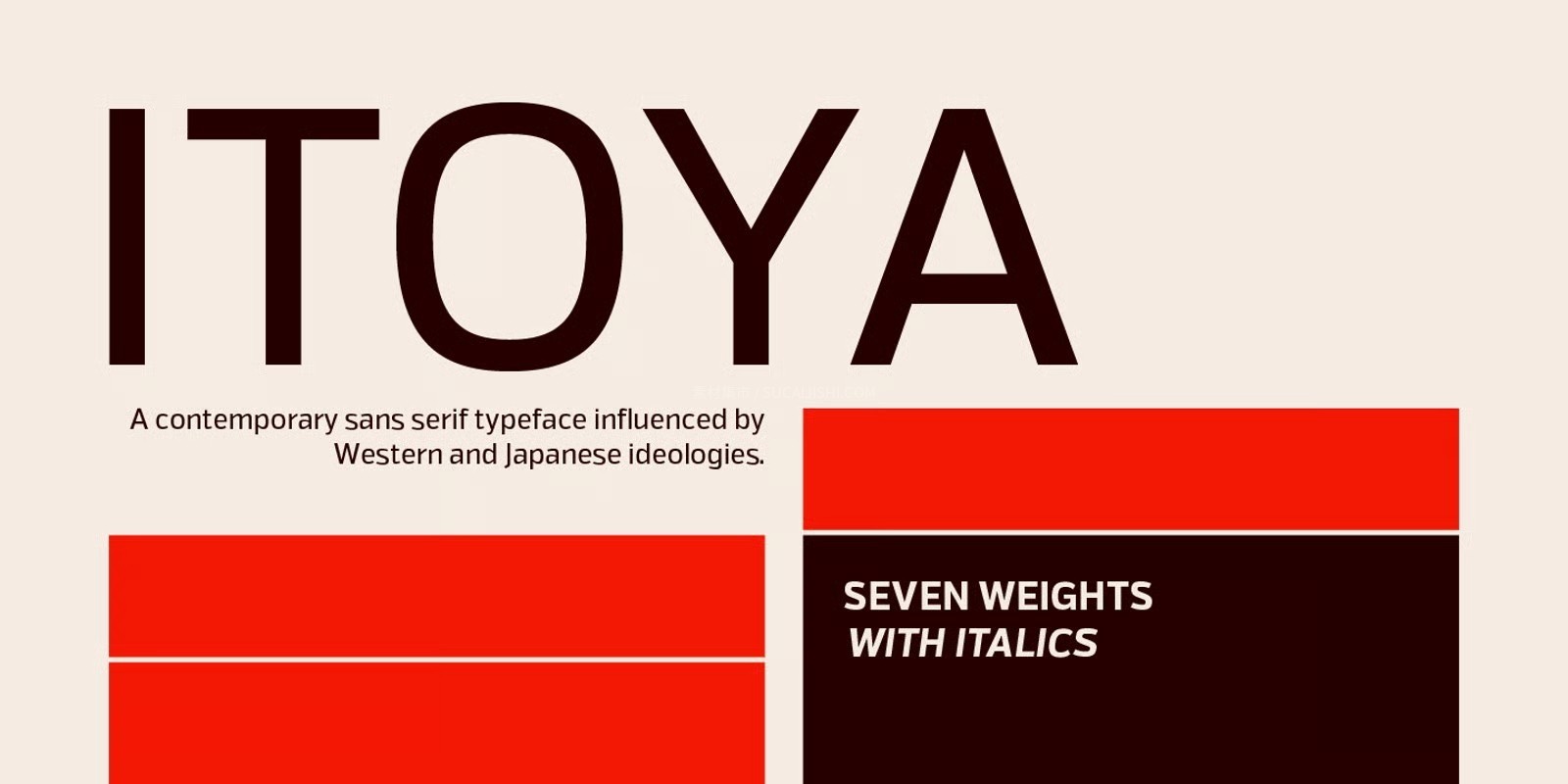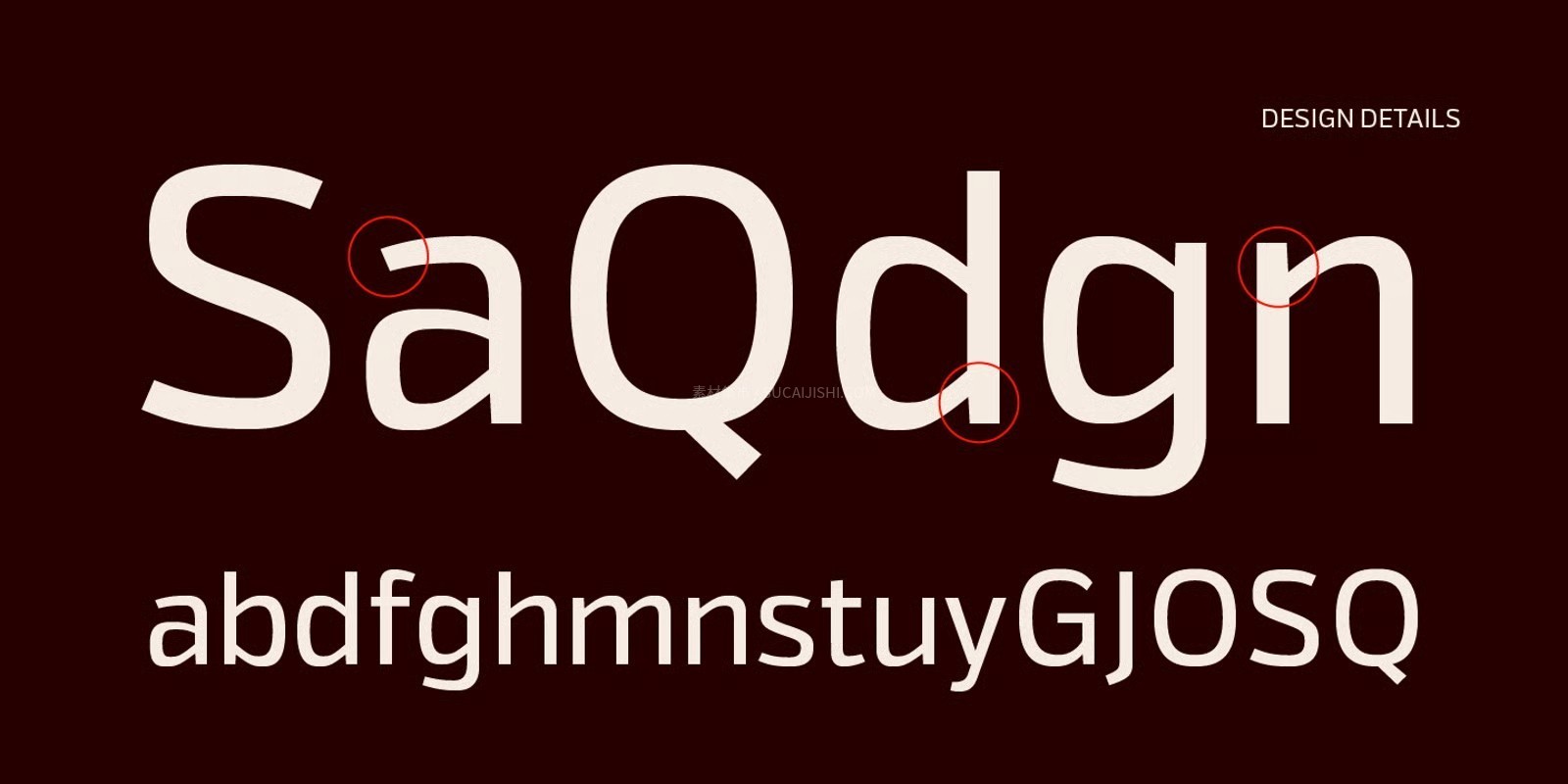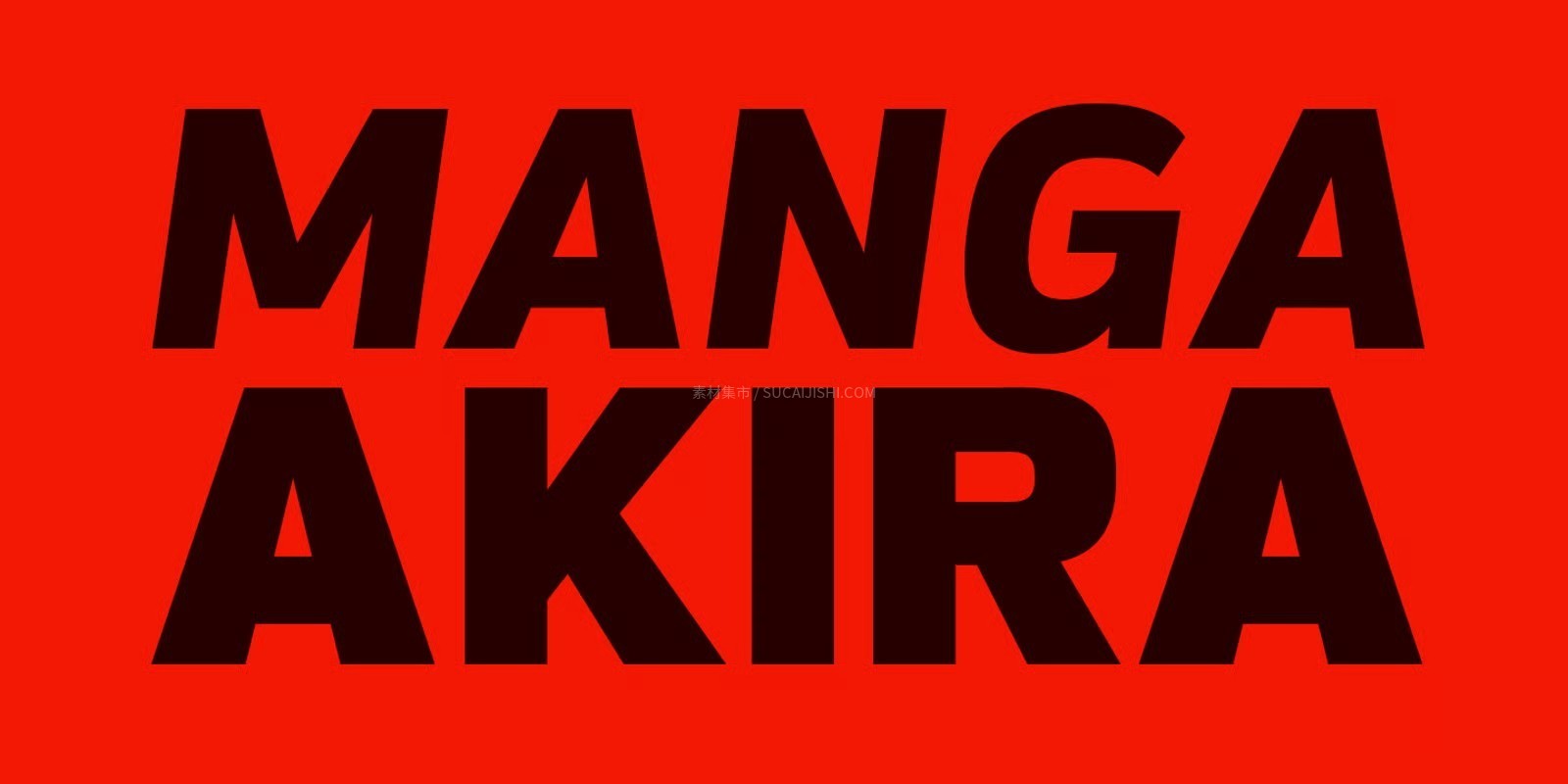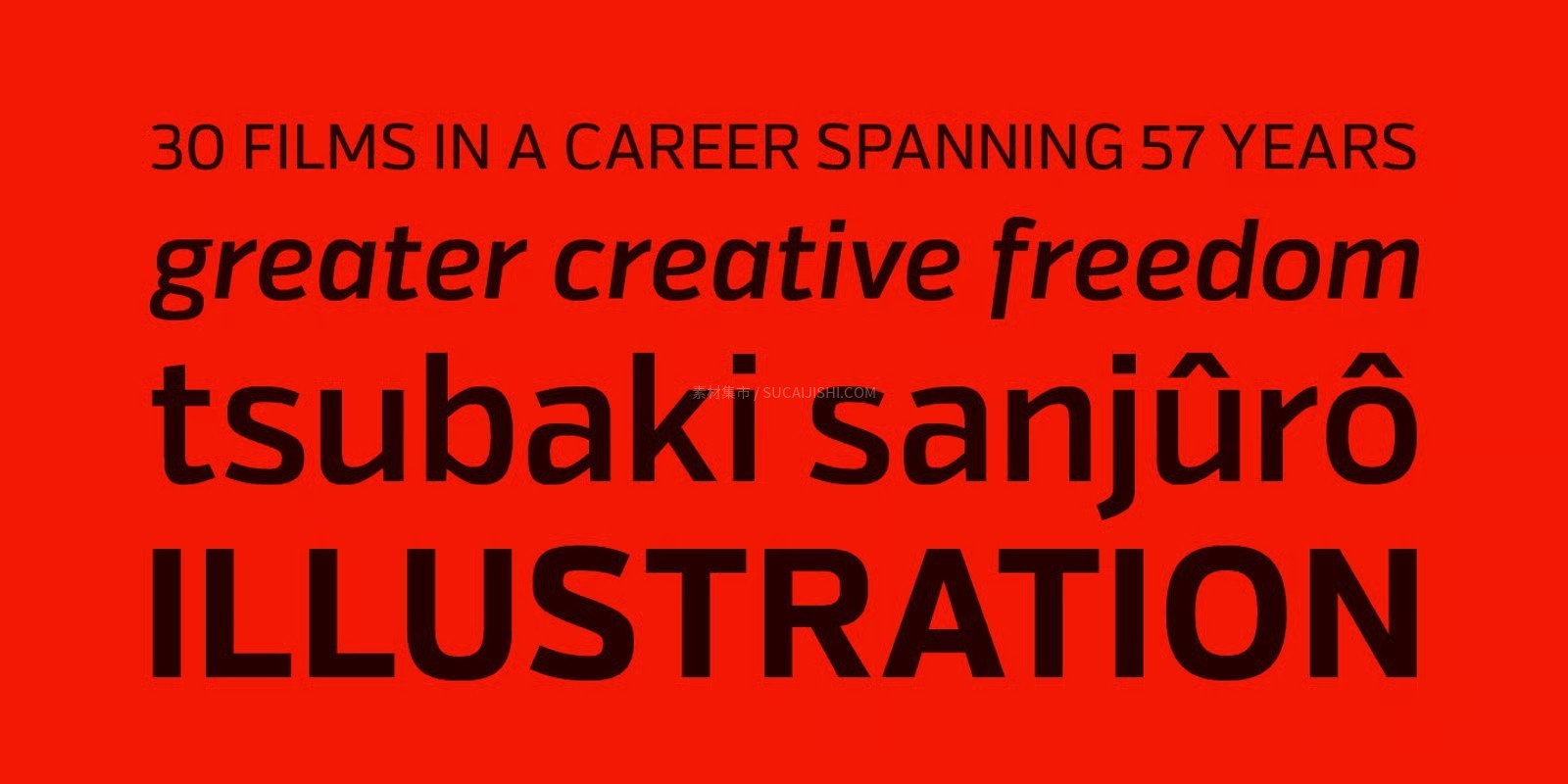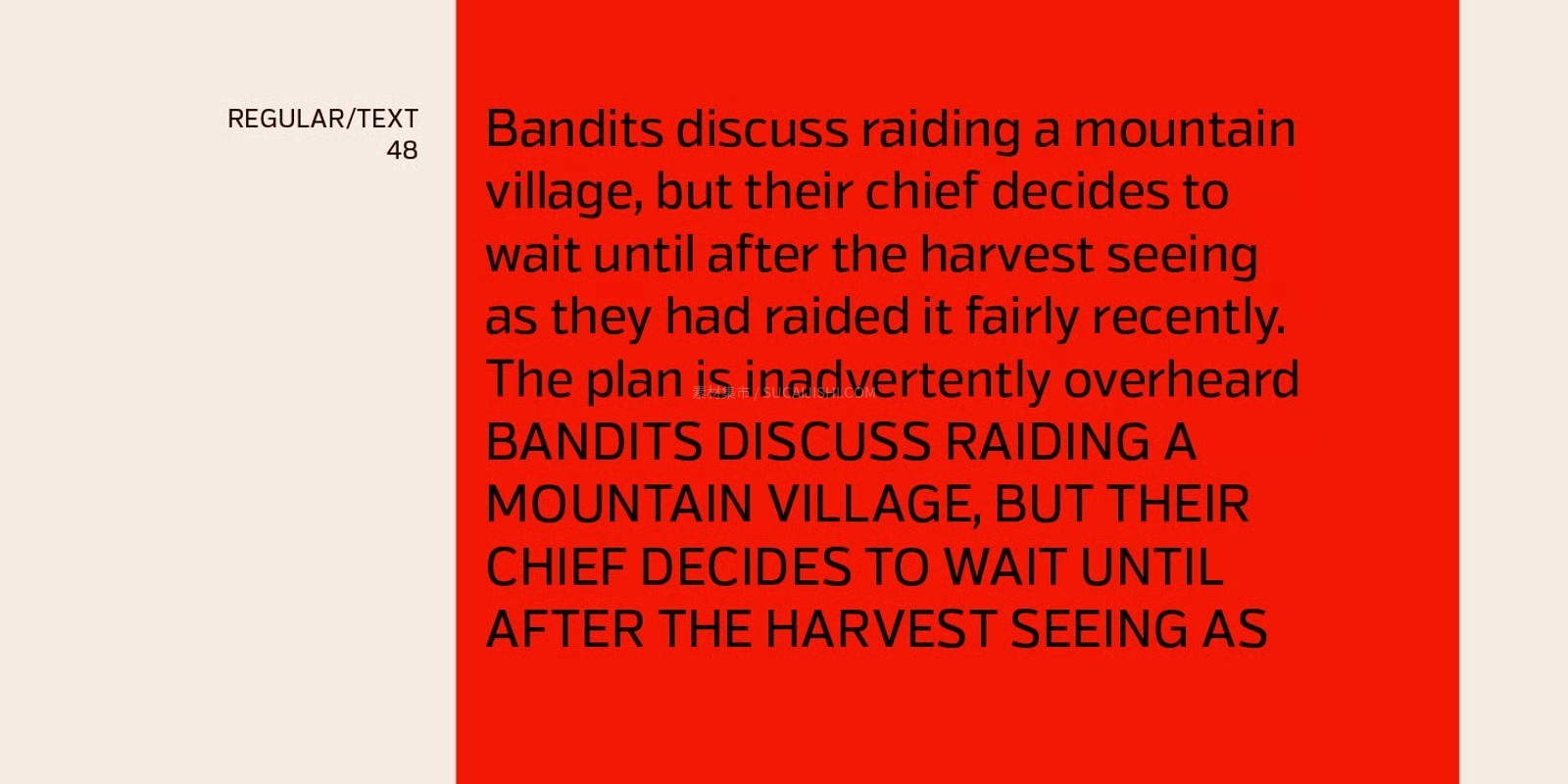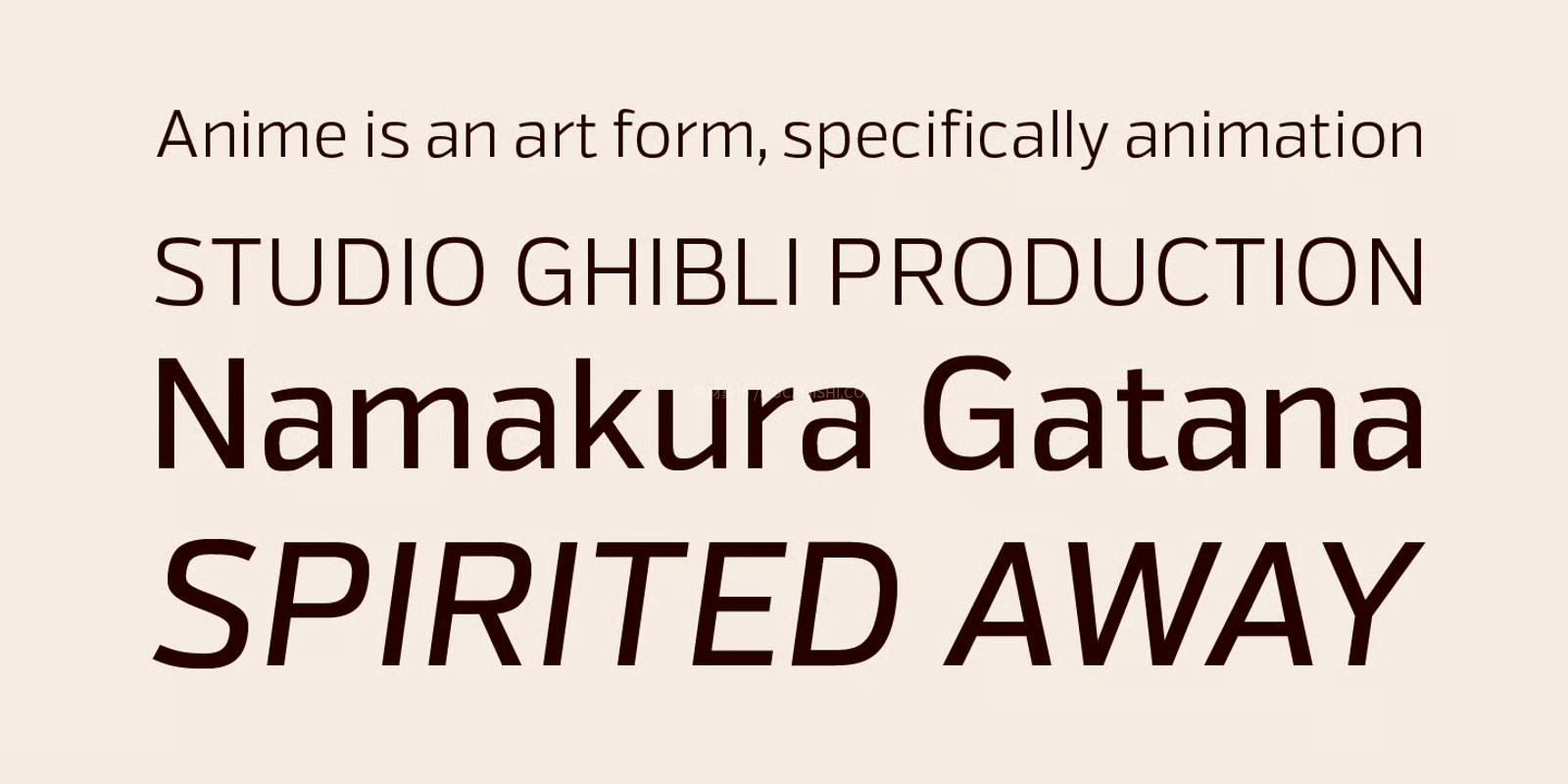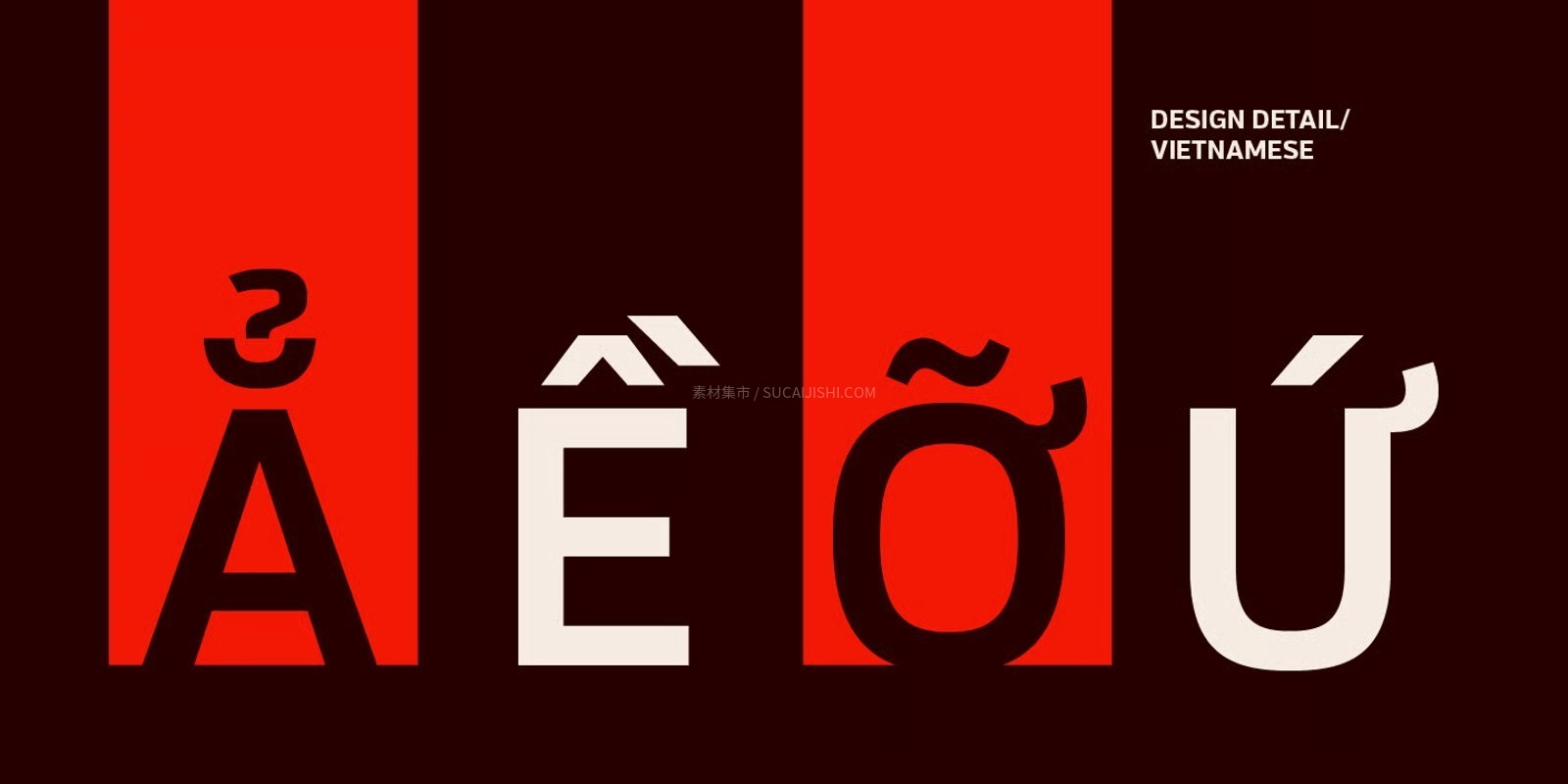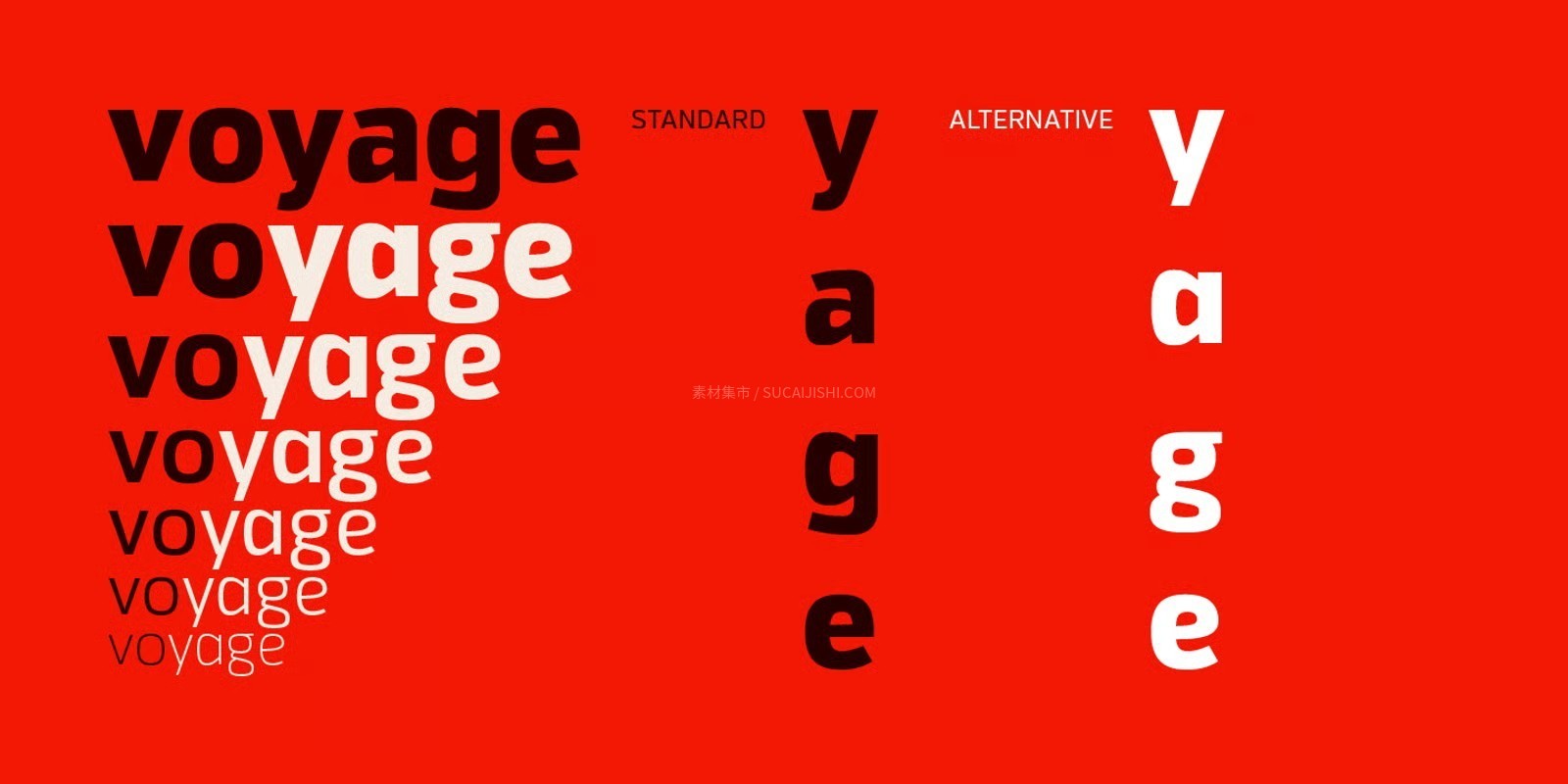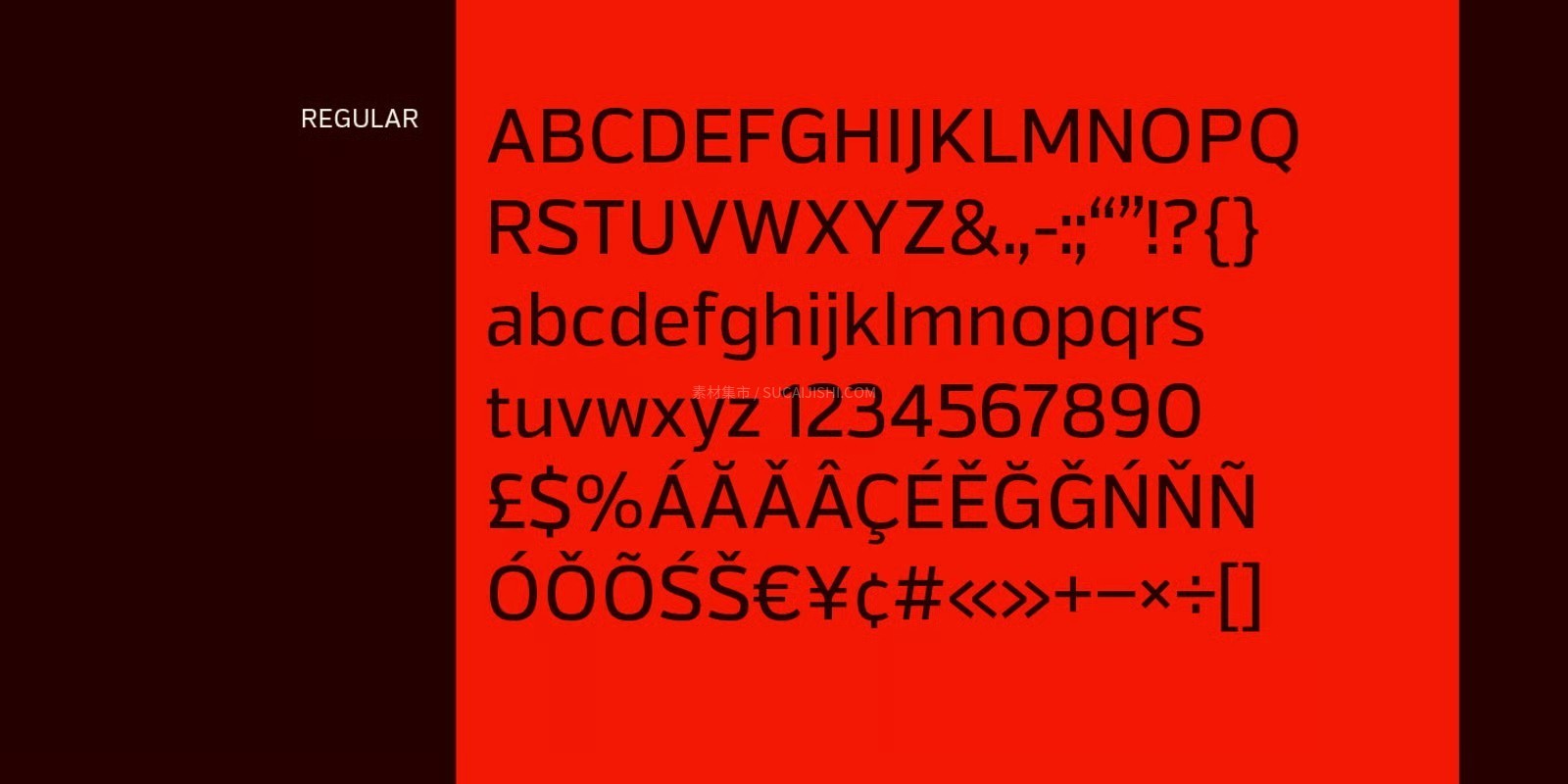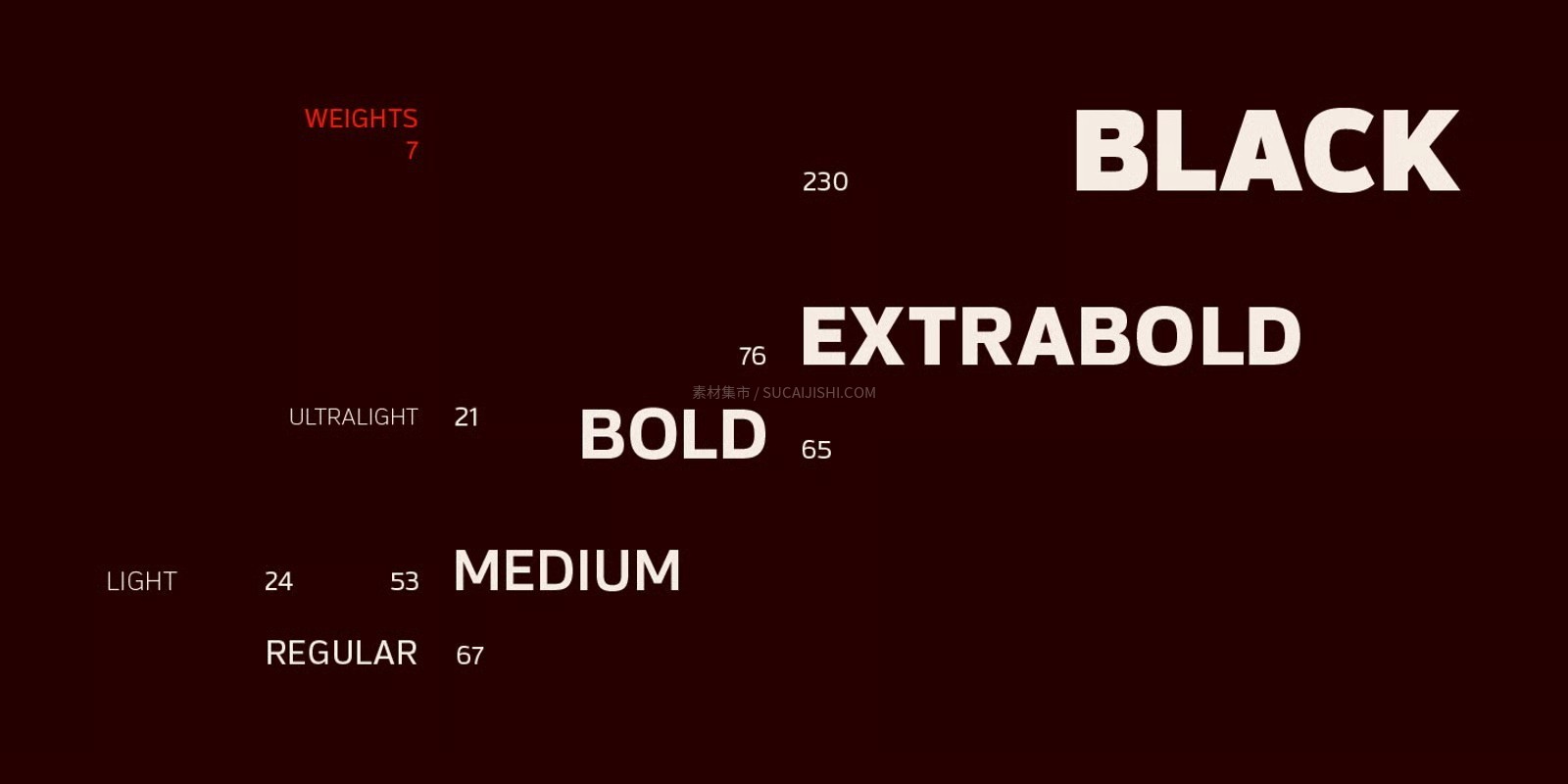
Itoya 现代无衬线英文字体
一款超级特别的宝藏字体——Itoya!它巧妙地融合了西方的精准机械感和日式美学的温润灵性,把现代功能性和情感表达平衡得刚刚好。这套字体自带一种锐利又现代的边缘风格,高级感直接拉满。整套资源非常良心,包含7种精选字重(甚至还有真正的草书斜体哦!),600多个字符,还贴心地提供了 a、e、g 和 y 的替代小写版本。再加上5种数字变体、连字、手动调整的完美字距以及全套 OpenType 功能,绝对是你字库里必不可少的排版利器,赶紧用起来吧!